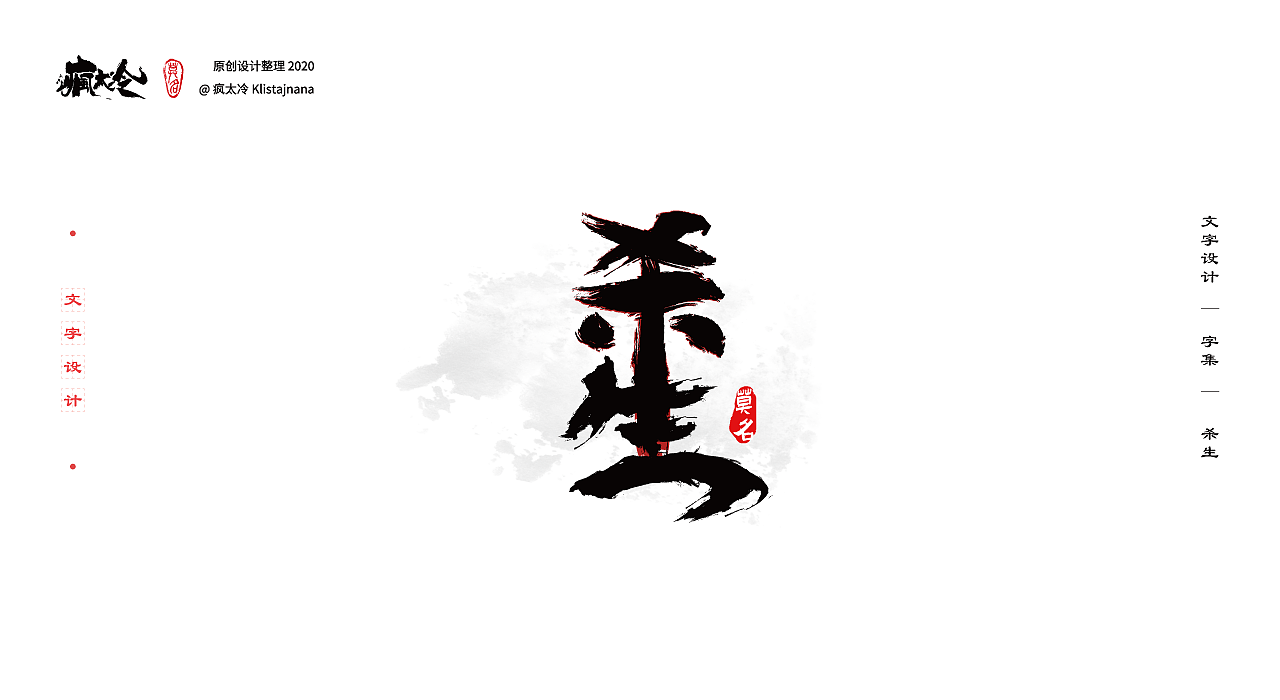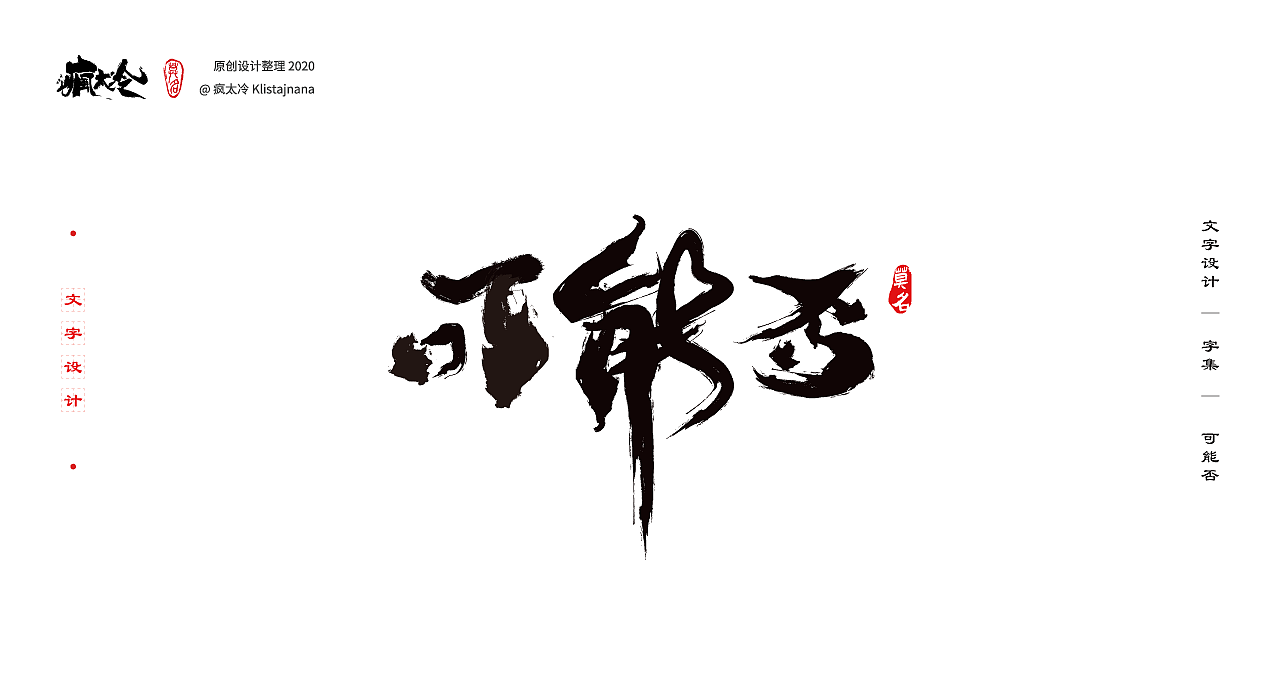
字集·字体设计·简单毛笔字第二波
我已洞彻字体设计的奥义,毛笔书法设计真的是功夫啊。
珍惜你身边会毛笔字的大佬吧,会书法是真的厉害。
做的好的字体设计,需要大量时间来磨砺技巧,
书法真的能在视觉和境界上分出层次,我时间有限,现在只能浅尝辄止
第二波的字体,我要展示真正的技术了(大佬忽视这句话就好)。